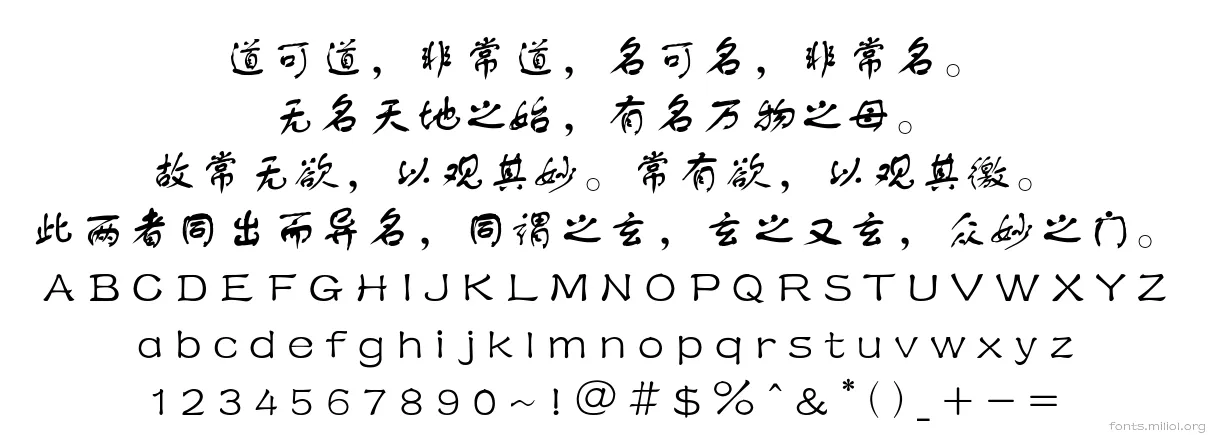
方正舒体简体 (FZShuTi-S05S) (FZSTJW--GB1-0) 字体下载
## 方正舒体简体:优雅与实用的完美结合
方正舒体简体是一款极具特色的中文字体,由方正字库精心设计开发。这款字体以"舒"为名,意在传达一种舒展、流畅的书写感受。其设计灵感源自中国传统书法艺术,将书法韵味与现代设计理念完美融合,创造出既典雅又实用的字体形态。
方正舒体简体的设计特点主要体现在以下几个方面:笔画舒展流畅,结构匀称自然,字形端庄大方。字体的横竖笔画粗细对比明显,转折处圆润自然,整体呈现出一种优雅而不失力度的视觉效果。这种设计既保留了传统书法的韵味,又符合现代印刷字体的规范要求。
在数字时代,方正舒体简体展现出独特的应用价值。其清晰的字形结构和适中的笔画粗细,使其在电子屏幕上具有良好的可读性。同时,字体的艺术美感又能提升数字内容的视觉品质,是传统与现代完美结合的典范。
### 一、方正舒体简体的视觉特性
方正舒体简体的笔画设计独具匠心。横画纤细流畅,竖画粗壮有力,形成鲜明的对比效果。转折处采用圆润处理,避免了生硬的直角转折,使字体整体显得柔和自然。这种设计既保证了字体的识别度,又赋予其独特的艺术美感。
在结构处理上,方正舒体简体注重字形的均衡与协调。每个字的重心稳定,部件之间的比例关系经过精心调整,确保整体视觉效果和谐统一。这种结构设计使字体在大小字号下都能保持良好的可读性。
字体的整体风格呈现出典雅大方的特点。既有传统书法的韵味,又符合现代审美需求。这种风格使其既能用于正式场合,又适用于创意设计,具有广泛的应用空间。
### 二、方正舒体简体的应用优势
在印刷品设计中,方正舒体简体展现出独特的优势。其清晰的笔画和优雅的形态,使印刷品显得精致而有品位。特别是在书籍封面、宣传册等需要突出设计感的场合,这款字体能有效提升作品的视觉品质。
在数字媒体领域,方正舒体简体同样表现出色。其适中的笔画粗细和清晰的字形结构,使其在各种电子设备上都能保持良好的显示效果。无论是网页设计还是移动端应用,这款字体都能为用户带来舒适的阅读体验。
在品牌形象塑造方面,方正舒体简体具有独特的价值。其典雅大方的风格能有效传达品牌的专业性和文化内涵,特别适合用于高端品牌的视觉识别系统设计。
### 三、应用场景与使用建议
在正式文档排版中,方正舒体简体能提升文档的视觉效果。建议用于标题、章节名称等需要突出显示的部分,但要注意与正文字体的搭配,保持整体的协调性。
在创意设计领域,这款字体能为作品增添艺术气息。可用于海报设计、广告创意等需要突出视觉效果的场合,但要注意与其他设计元素的配合,避免过度使用导致视觉疲劳。
在商业宣传材料中,方正舒体简体能有效提升材料的品质感。适合用于企业宣传册、产品手册等需要展现专业形象的场合,但要注意字号的合理使用,确保信息的有效传达。
方正舒体简体是一款兼具实用性与艺术性的优秀字体。其独特的设计特点和广泛的应用价值,使其成为设计师和文字工作者的理想选择。在未来的设计实践中,这款字体必将发挥更大的作用,为视觉传达领域注入新的活力。